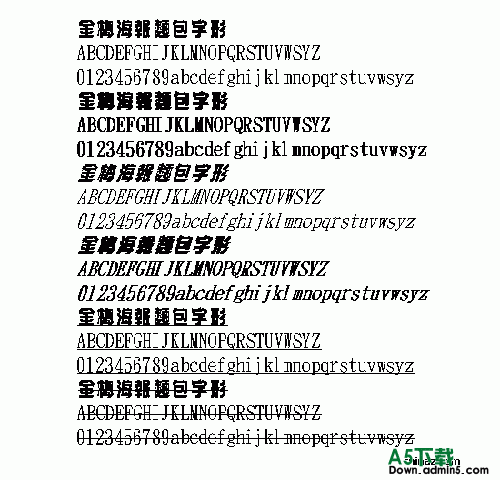
軟件介紹 軟件標簽: 金梅海報面包字形 字體 金梅海報面包字形(繁)是一個專門用來設計海報廣告的繁體字形,字體圓潤飽滿,需要的朋友快來綠色資源網里下載試試吧!金梅海報面包字形(繁)文件說明金梅海報面包字形是文鼎字體庫中一種字體,常用于美工設計方面,喜歡的朋友不要錯過。金梅海報面包字形(繁)安裝方法Win 7\Win 8\Win 10系統 : 鼠標右鍵單擊字體文件,然后點擊 > "Install" 安裝字體 Win XP(2000\98)系統 : 把解壓好的字體文件放入 C:\Windows\Fonts 目錄中即可 蘋果(APPLE)Mac OS系統 : 下載好后雙擊字體,然后選擇:安裝字體 軟件截圖 上一張下一張(1 / 1) 安裝詳細截圖 猜你喜歡 海報字體 金梅字體 海報字體 海報字體是常用于海報設計的字體,主要包括了pop海報字體、海報中文字體、海報英文字體三種。基本上所有的海報上都有字體,所以,海報制作的朋友們就需要使用到各種常用的海報字體,綠色資源網為大家準備了不少,趕快下載體驗吧! 查看更多>> 海報字體40款打包 233.20M/中文/1.4/ttf免費版下載 華康海報體w12 1.53M/中文/5.7/ttf簡繁合并版下載 華康海報體w12p 1.53M/中文/10.0/ttf版下載 華康海報體W9繁體 3.56M/繁體/10.0/下載 華康華康海報體W12繁體 3.26M/繁體/5.3/下載 超研澤海報體繁體 1.27M/繁體/10.0/下載 金梅字體 金梅字體是以繁體字形為主,多數的金梅字體都是繁體。金梅字體給人的感覺比較多樣,有的比較圓潤,有的比較可愛,還有破裂的字體,于楷體形成了鮮明的對比,沒有固定的樣式。金梅字體多用于廣告制作、海報制作、封面制作等。 查看更多>> winman tun10011字體 17.57M/中文/6.6/下載 金梅浪漫原體國際碼 1.91M/中文/6.6/下載 金梅粗明原體國際碼 1.41M/中文/5.0/下載 金梅流行書 2.78M/中文/10.0/下載 金梅綜藝菱心 4.19M/中文/10.0/下載 金梅浪漫小胖 3.44M/中文/10.0/下載 其他版本下載 標題 大小 更新日期 下載 下載地址 電腦版 金梅海報面包字形(繁) 點擊報錯 軟件無法下載或下載后無法使用,請點擊報錯,謝謝! 關閉報錯反饋 請描述您所遇到的錯誤,我們將盡快予以修正,謝謝! *必填項,請輸入內容 本類最新 金梅海報美工體 金梅新箭頭字范例字體 免費版 金梅特黑水花字形字體 免費版 金梅粗尖頭字范例繁體字體 免費版 金梅淡古字ttf 免費版 金梅浪漫鏡射體 相關文章 Photoshop字體安裝使用方法和技巧 如何解決“無法新增字體”問題 Win 7系統安裝字體方法 網頁字體大小設置方法 怎么改網頁字體大小 在Linux系統中安裝字體的幾種方法 windows7字體顯示問題:打開某些程序的時候顯示的是亂碼 用戶評論 熱門評論 最新評論 發表評論 查看所有評論(0) 昵稱: 請不要評論無意義或臟話,我們所有評論會有人工審核. 字數: 0/500 (您的評論需要經過審核才能顯示)